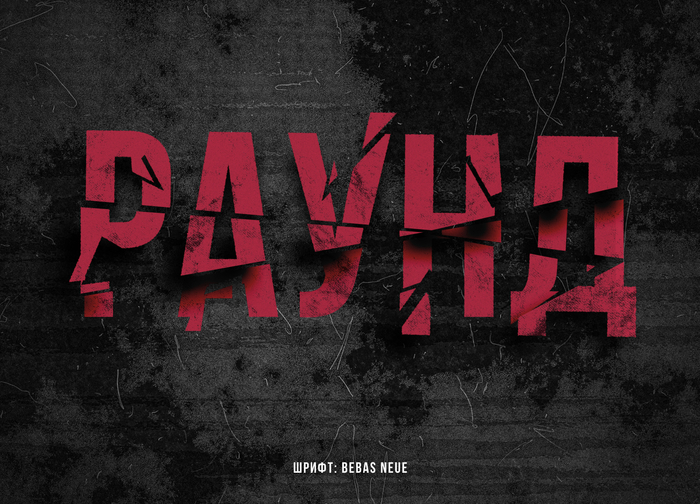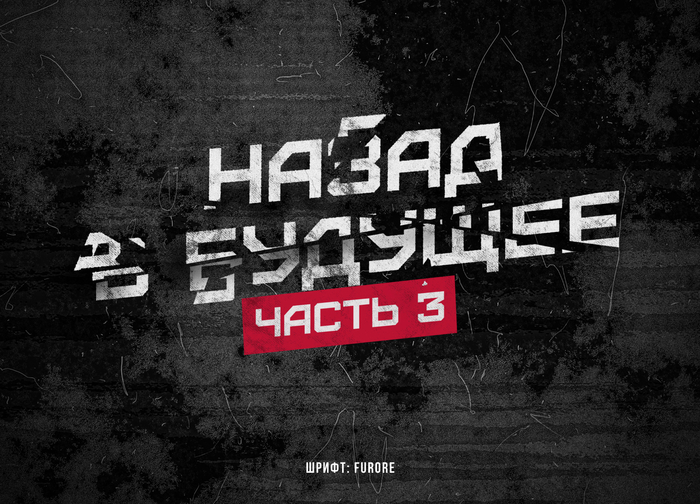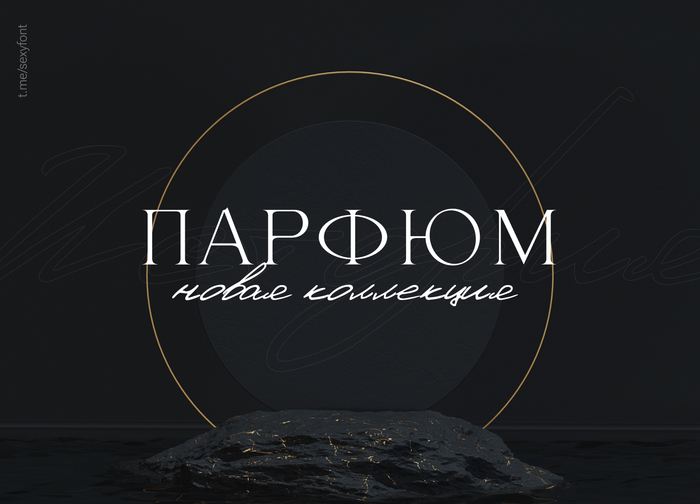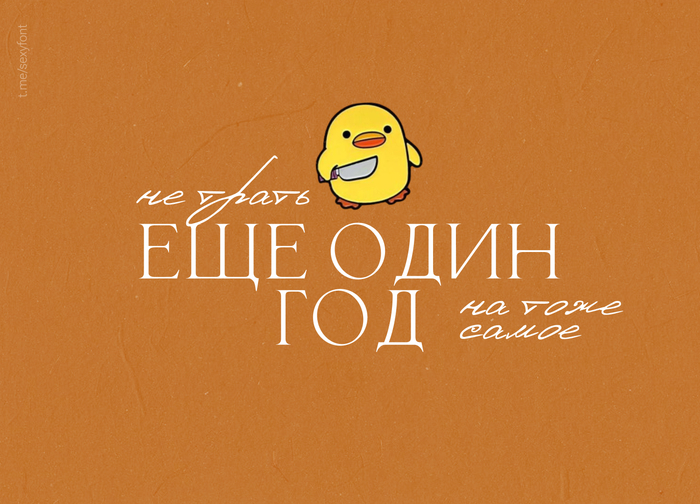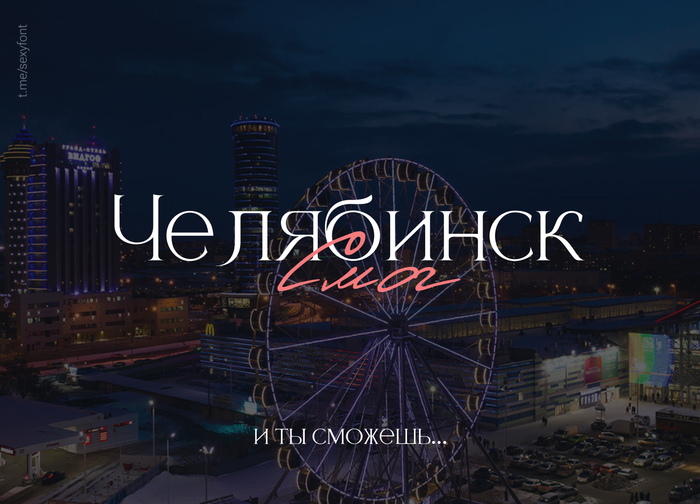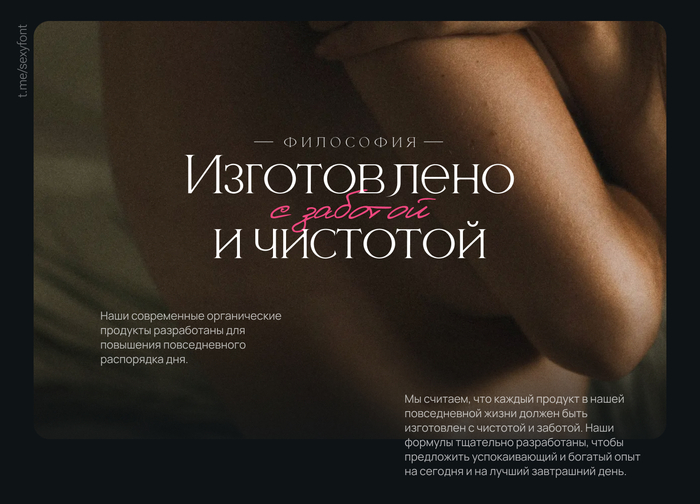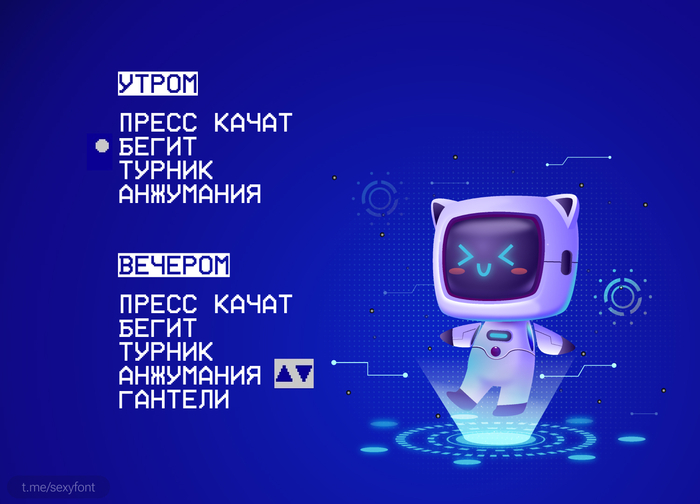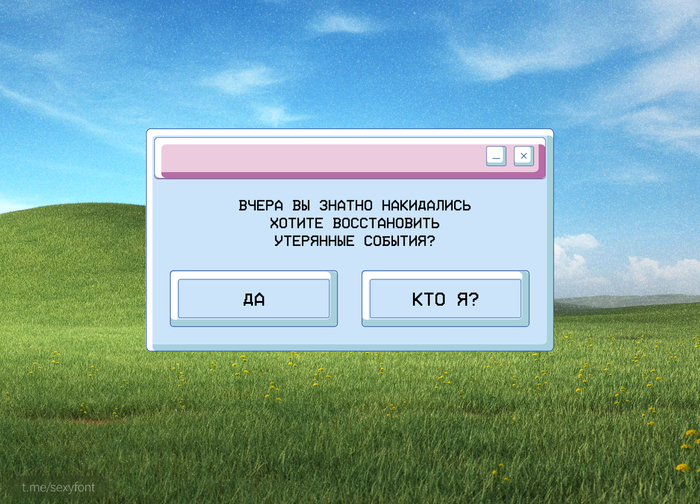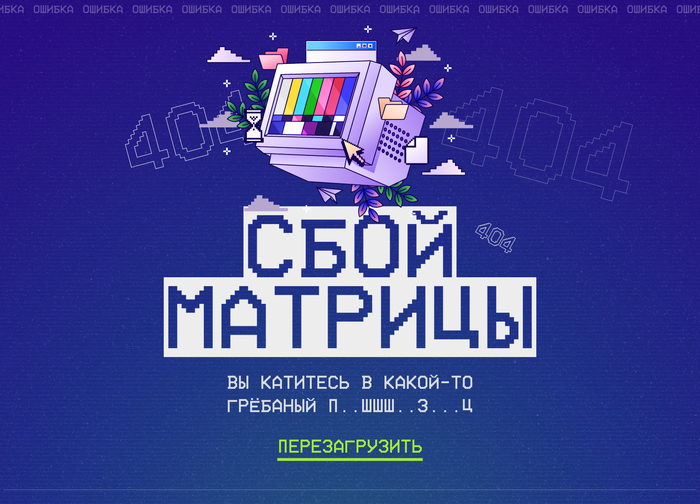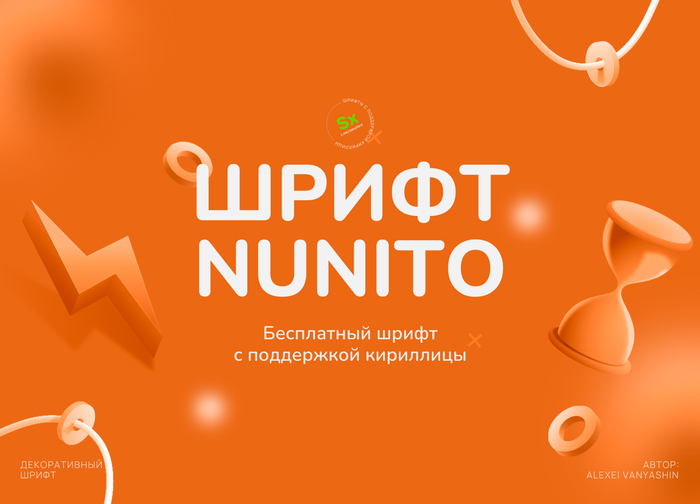
Шрифт birdy
Шрифт birdy. Красивый декоративный шрифт для заголовков. Нравится, как отличаются строчные и прописные буквы) Из можно легко чередовать в каждом слове.
Бесплатный шрифт Nuqun
Nuqun — бесплатная декоративная гарнитура cо строгой геометрией. Чистый и лёгкий в чтении, шрифт станет фундаментом вашей дизайн-системы: подойдёт для вывесок, рекламных плакатов и меню
Текстовый эффект broken
Давненько у нас не было текстовых эффектов) Держите, распишитесь. Разбитый эффектик. Для использования подойдут практически любые шрифты, но лучше всего высокие и жирные. Названия указал внизу каждой карточки. Как пользоваться эффектом записывал на ютубчике
Шрифтопара Berold и Denistina
Иииии 16-й выпуск рубрики шрифтопары. Сегодня вашему вниманию антиква Berold и рукописный Denistina.
Шрифт Homevideo. Пиксели
Homevideo. Пиксельный шрифт со странным названием) Что-то со временем старых операционок или приставки денди.
Шрифт Nunito
Шрифт Nunito. Или «Нунитооооо!» Фраза которую не хочется услышать от заказчика 😂 А если серьезнее. То ловите хорошо читаемый, вариативный гротеск. Есть 2 варианта: с мягкими краями и более острыми. (Добавил оба) В отличие от того же монтсеррата он более компактный по ширине.